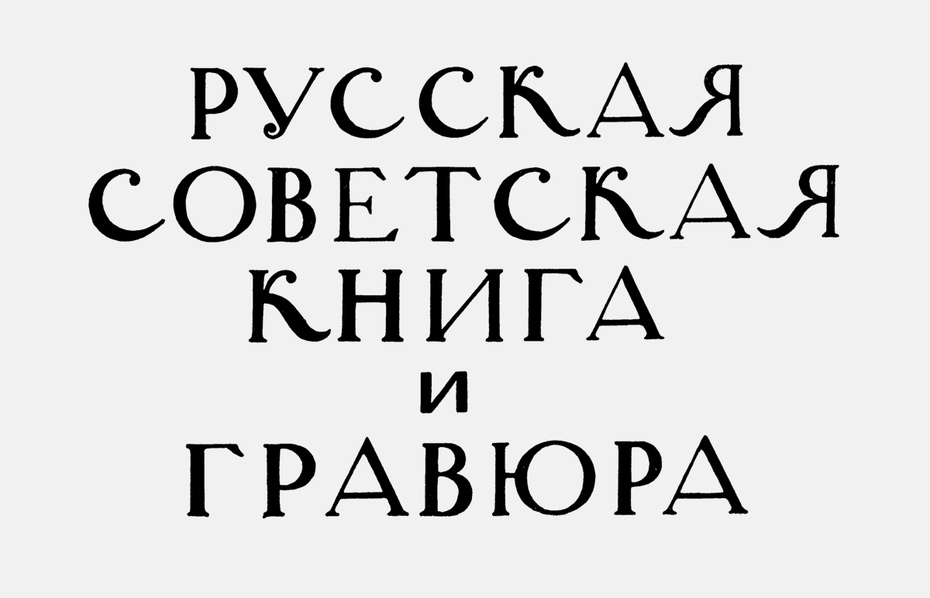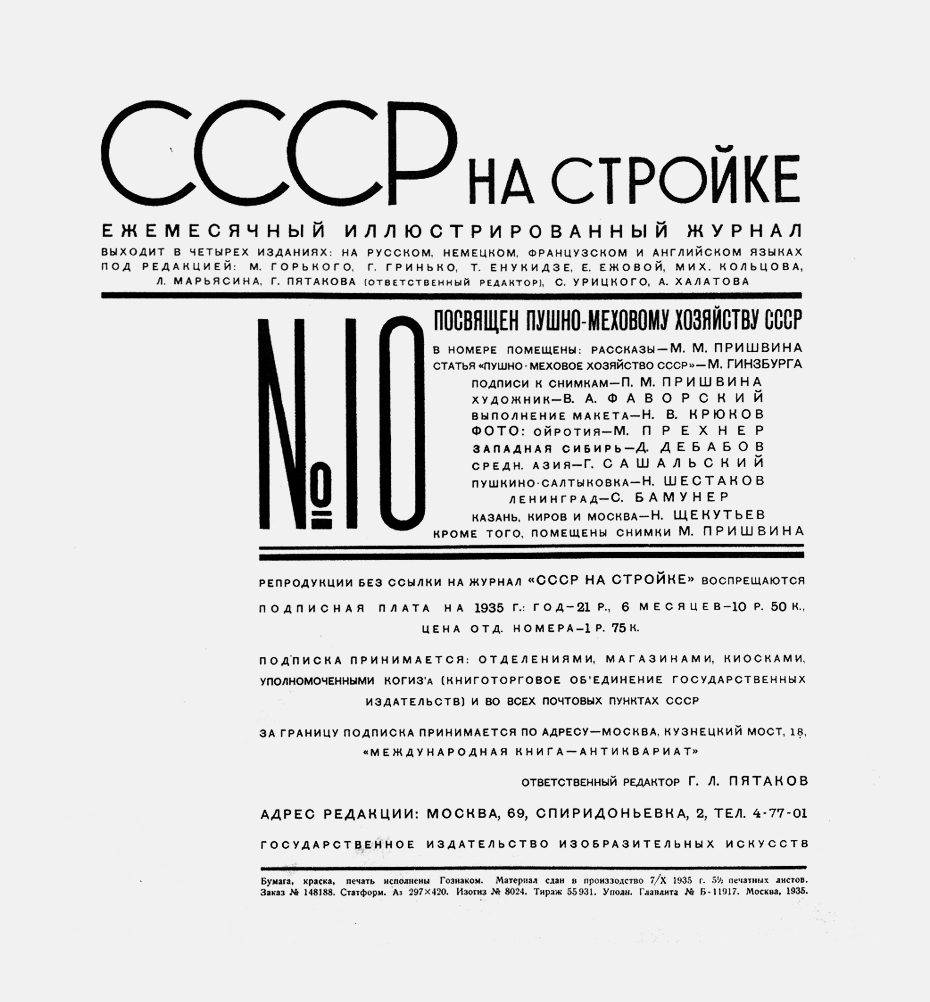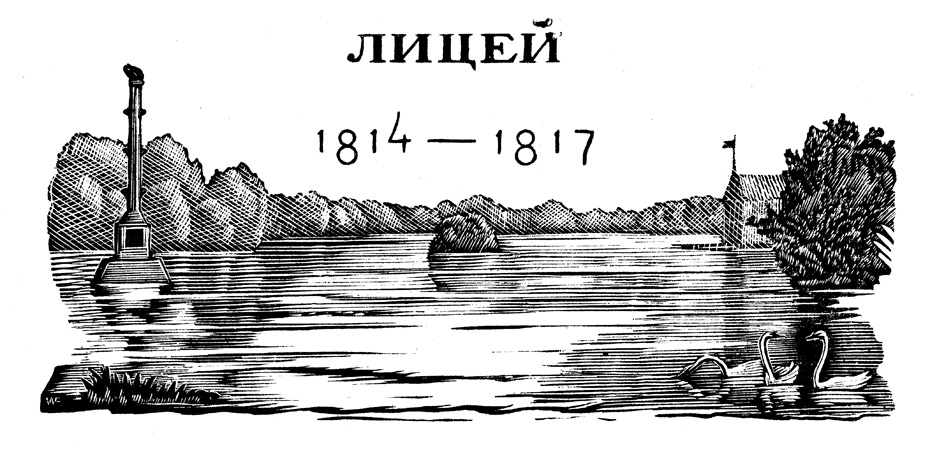
О шрифте
Владимир Фаворский был мастером гравированного акцидентного шрифта, который он использовал в сочетании и в неразрывной связи с изображениями на титульных листах и обложках книг и журналов. Его шрифт самобытен и многолик, с помощью чёрного и белого он вместе с изображениями передаёт сложность и многообразие окружающего нас пространства. Подход Фаворского к шрифтовым композициям разительно отличается от подхода его современников, как отечественных (Николай Пискарёв, Алексей Кравченко), так и зарубежных мастеров ксилографии, работавших с гравированным шрифтом (Эрик Гилл, Рейнольдс Стоун). Его работам присуща небывалая свобода в композиции и новаторство в трактовке форм. Зачастую он смешивает разные шрифтовые стили на одном листе, а иногда и в одном слове, предвосхищая поиски дизайнеров постмодернизма. Глава «О шрифте» из статьи «О графике как об основе книжного искусства» позволит читателю познакомиться с небольшой частью теории композиции Фаворского, не имеющей аналогов в зарубежной литературе. В главе он излагает собственную классификацию шрифтов и виды им соответствующих изображений и представляет в неожиданном ракурсе ключевые понятия, которыми мы пользуемся и сегодня в графическом дизайне и типографике.
Владимир Фаворский
аша русская шрифтовая система — одна из европейских систем, идущая отчасти от греческой, — в выражении и оформлении своих функций очень сильно использует вертикаль и горизонталь со всеми их свойствами. Причём можно сказать, что и горизонталь как линия равномерного движения, и вертикаль как ограниченная, остановленная линия, могущая иметь свой определённый внутренний строй и отсюда свой определённый масштаб, выявляют в нашем шрифте все основные свойства.
Горизонталь составляет основу строки, функция движения по тексту, в частности по строке, использует свойства горизонтали, её равномерное движение, и естественно и увлекательно вместе с буквами идёт по ней. С другой стороны, вертикаль столбца даёт нам и цельность этого столбца, когда мы его воспринимаем статически, и, читая строку за строкой, мы спускаемся по ней все ниже и ниже, и, между прочим, это движение вниз по вертикали, идя как бы против течения, идущего снизу, и имея тем самым всё время упор, может быть всегда остановлено. (Это подобно тому, как пароход, положим, на реке Оке, идя против течения, легко останавливается и задерживает ход и ссаживает пассажира, а идя по течению, часто отказывается это сделать.)
Но вертикаль со всеми её свойствами как ограниченной и масштабной линии работает в шрифте главным образом как остановка. И в книге вертикаль титула и вертикаль столбца, и в букве вертикаль штамба буквы работает как остановка.
Оформление этих двух основных моментов в шрифте и составляет главное, и в этом вертикаль и горизонталь играют первостепенную роль.
В. Фаворский. «Шрифт, его типы и связь иллюстрации со шрифтом». Обложка. 1925. Ксилография.
Если взять слова нашего языка, то для всех ясно, что они не безразличны к содержанию своему и являются большею частью живыми словесными изображениями тех вещей, которые они обозначают.
Не являются ли буквы тоже сколько-то подлинным изображением тех голосовых жестов, которыми мы при помощи горла, нёба, зубов и языка произносим нужный нам звук?
В этом отношении можно по-разному расценивать гласные и согласные звуки. Гласные гораздо проще по мускульному жесту; тут участвует главным образом голосовая труба, которая либо сжимается, как в звуке «И», либо берётся открытая в самой своей глубине, как в звуке «А», либо удлиняется ртом в звуке «О», либо удлиняется губами в звуке «У». Поэтому естественно, что в буквах это отражается.
В. Лазарев. «Никодим Павлович Кондаков». Обложка. 1925. Ксилография.
В буквах, обозначающих гласные звуки, изображается как бы голосовой жест — это ясно в «О», ясно в «У», ясно в «И», если бы изображать его однопалочным; несколько менее ясно в букве «А», а в букве «Е», особенно если нарисовать её, как «Э» оборотное, как бы в профиль, изображается весь голосовой аппарат — и рот, и язык.
С согласными дело обстоит гораздо сложнее, и угадать там изобразительный момент труднее. Но мы, во всяком случае, можем воспользоваться различием между гласными знаками и согласными. Первые у нас в шрифте по преимуществу зияющие, а вторые главным образом строятся на штамбах, кроме немногих, как «З» и «С».
«Революционная поэзия современного Запада». Антология. Обложка. 1928. Ксилография.
Между прочим, в древних шрифтах существовало значительное различие между гласными и согласными знаками.
В латинском шрифте, писавшемся на памятниках архитектуры, гласные были более широкими и более зияющими, чем согласные, а в древнем славянском гласные, наоборот, сжимались, предпочтение оказывалось согласным, которые вносили в речь как бы цвет, а модуляции гласных могли рассматриваться как количественные изменения; поэтому гласные знаки сжимались, кроме, может быть, «У», а согласные часто были даже очень широкими, как «М» и другие буквы.
«Слово о полку Игореве». Заглавие для переплёта. 1938. Ксилография.
Для нашего языка характерно открытое звучание гласных, и поэтому естественно обратить внимание на их различие от согласных и в их графическом написании. Если это сделать, то можно понять и начертание слога как чего-то цельного.
Здесь надо заметить, что иногда стремились в шрифте дать по возможности буквы одинаковой ширины, но в древних шрифтах к этому никогда не стремились, и это было бы и не на пользу дела, так как выразительность шрифта при общем единстве масштаба, стиля и элементов, как то: штамбов, дуг и ветвей — основывается на различии букв, на разной их выразительности, и если мы можем не только каждую из них различить друг от друга, то тем более полезно отличить графически гласные от согласных.
Наши согласные знаки вносят в шрифт массу штамбов вертикальных мачт. У нас много букв с одной мачтой, но есть и с двумя, есть даже с тремя — как «Ш» и «Щ»; и даже в гласных мачта занимает некоторое место — как в «И» и в «Ы» и «Е»; и в мягком и твёрдом знаке, и в двугласных — как в «Ю» и «Я».
То же, что основ­ной штрих — до­ми­ни­ру­ю­щий вер­ти­каль­ный или на­клон­ный штрих в осно­ве зна­ка. В округ­лых зна­ках основ­ной штрих на­зы­ва­ет­ся на­плыв (мак­си­маль­ное утол­ще­ние штри­ха). — Прим. ред.
В. А. Фа­вор­ский так на­зы­ва­ет за­сеч­ки. — Прим. ред.